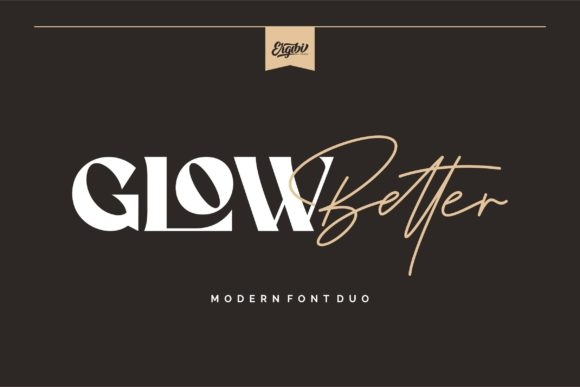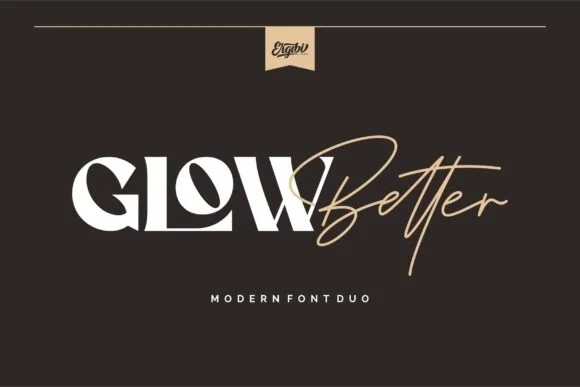
[Creativefabrica] Glow Better Font (2021)
Название: Glow Better Font (2021)
Glow Better
- это прекрасный дуэт шрифта (засечки и шрифта), созданный для придания стильности вашим заголовкам и логотипам.
Этот шрифт читается как сильный, уверенный и динамичный и может добавить тонны ностальгического характера в ваши проекты.